안녕하세요. 무엇입니다. 오늘은 정말 흥미로운 소식을 가지고 왔어요. 서울시에서 청소년들이 직접 만든 서체 4종을 무료로 배포한다는 소식인데요, 이 폰트들은 저작권 걱정 없이 무료로 사용할 수 있다고 합니다! 그럼 저와 함께 청소년들이 만든 서체와 다운로드 방법을 알아보겠습니다. 🌟 뉴스기사를 통해 세상을 알아보는 무엇!
서울시 청소년들의 놀라운 창작물 🖌️
서울시립청소년미디어센터에서는 청소년들이 글꼴 개발 전문기업과 함께 서체를 직접 개발했어요. 이들이 만든 서체는 '귀여우면다야체', '손글씨체', '시티팝체', '오뉴월꽃나무체' 등 다양한 매력을 지닌 4종이에요. 이 서체들은 무료로 배포되며, 누구나 저작권 걱정 없이 자유롭게 사용할 수 있다고 해요. 👏
청소년들의 창의력과 열정의 결실 🌈
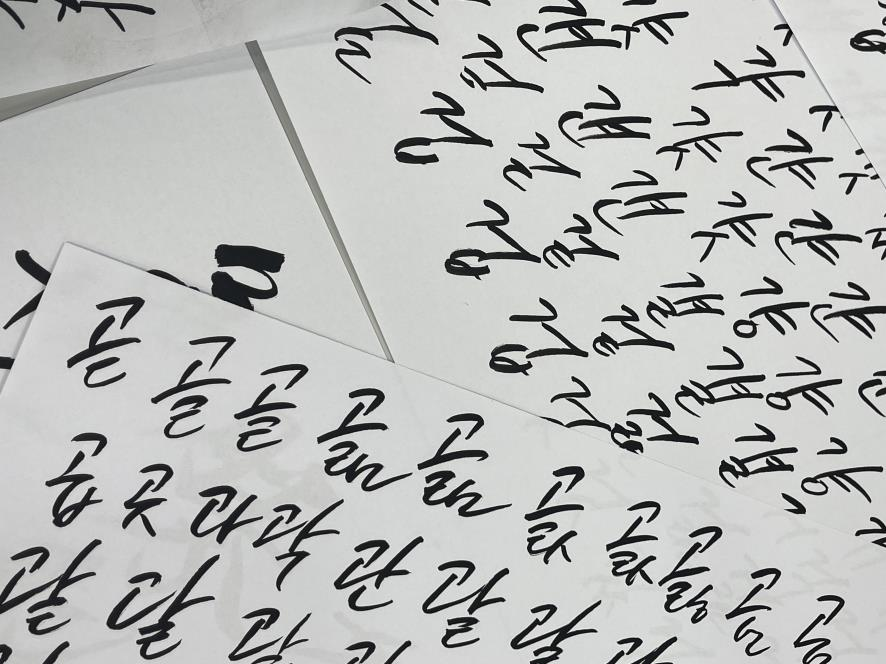
이번 프로젝트는 청소년들이 서체 디자인의 전 과정을 경험하며, 자신들의 아이디어를 현실로 만들어낸 멋진 사례예요. 이들은 전문가의 이론 및 실습 교육을 통해 서체와 이모티콘 등 다양한 공공디자인 결과물을 완성했답니다.
무료로 만나볼 수 있는 서체들 📝
이번에 배포되는 서체들은 각각의 제작자가 자신만의 개성과 창의력을 담아 만들었어요. 예를 들어, '귀여우면다야체'는 최한별 작가의 손글씨를 바탕으로, '오뉴월꽃나무체'는 장혜리 작가가 가시 없는 장미에서 영감을 받아 제작했죠.
서체 개발 전시회도 놓치지 마세요! 🖼️
그리고 서울시립청소년미디어센터 1층에서는 이번 서체 개발 과정과 청소년 디자이너들의 다양한 작업물을 전시하고 있으니, 이 기회에 꼭 방문해보세요!
마무리하며